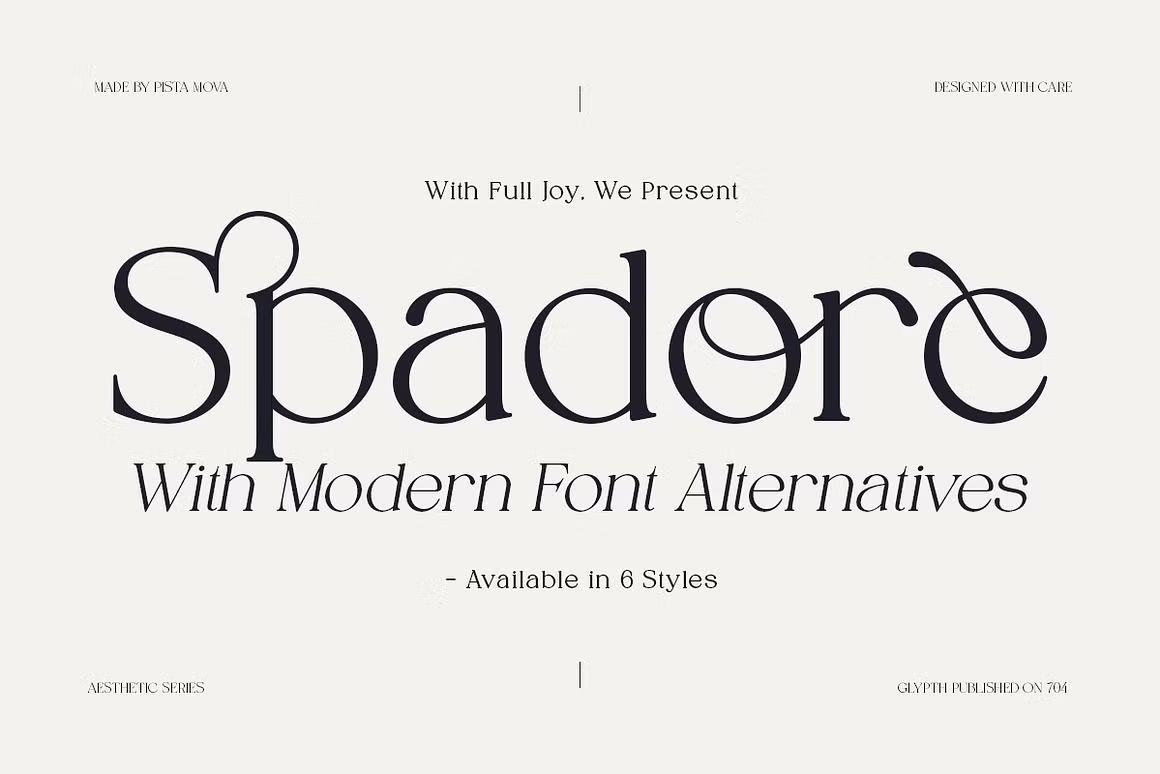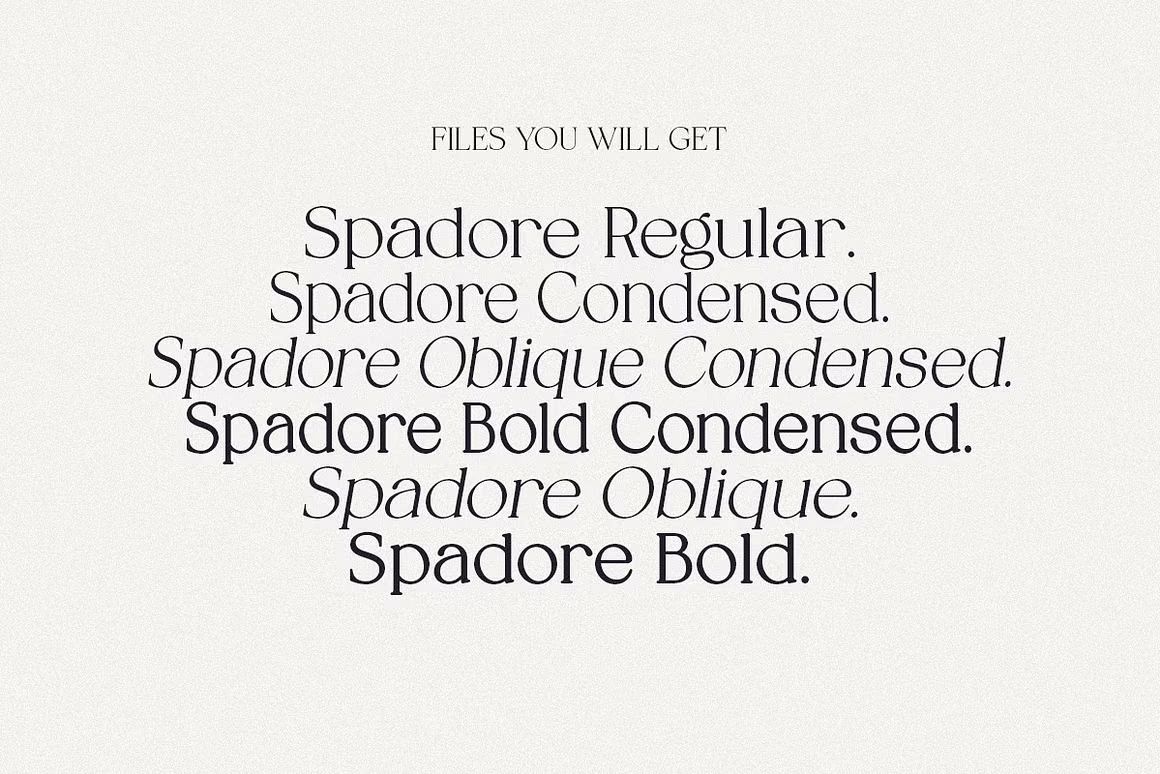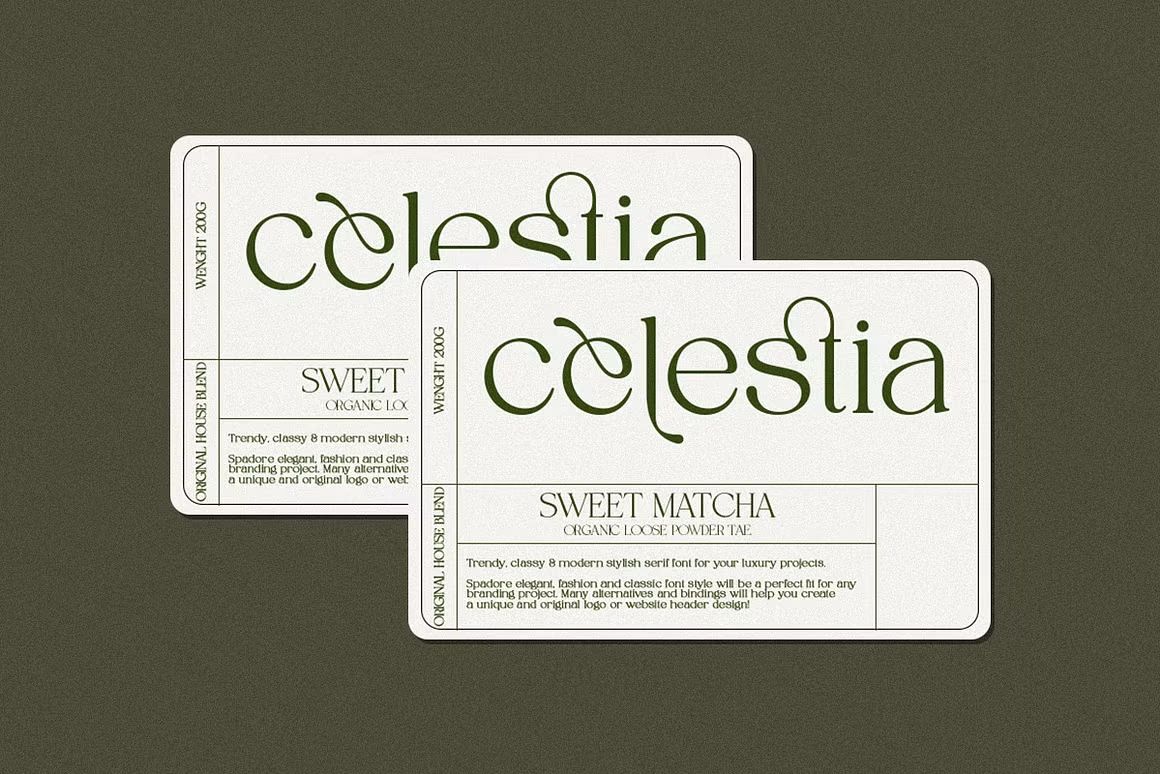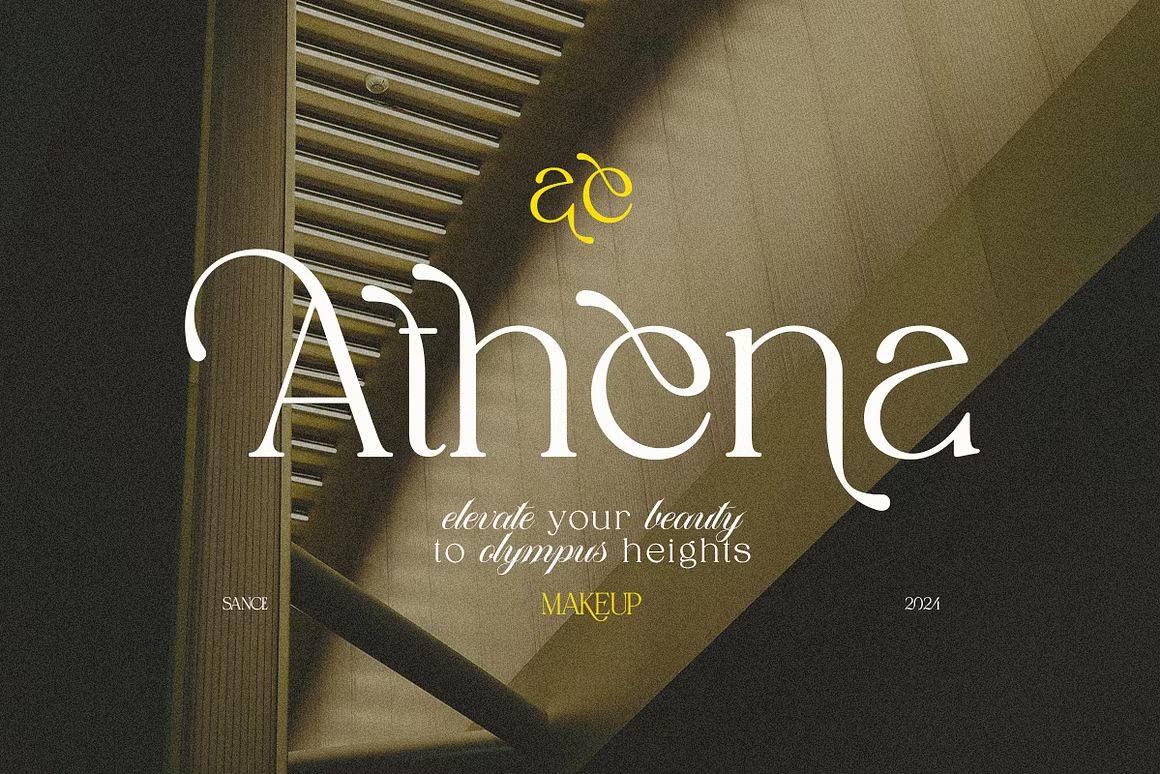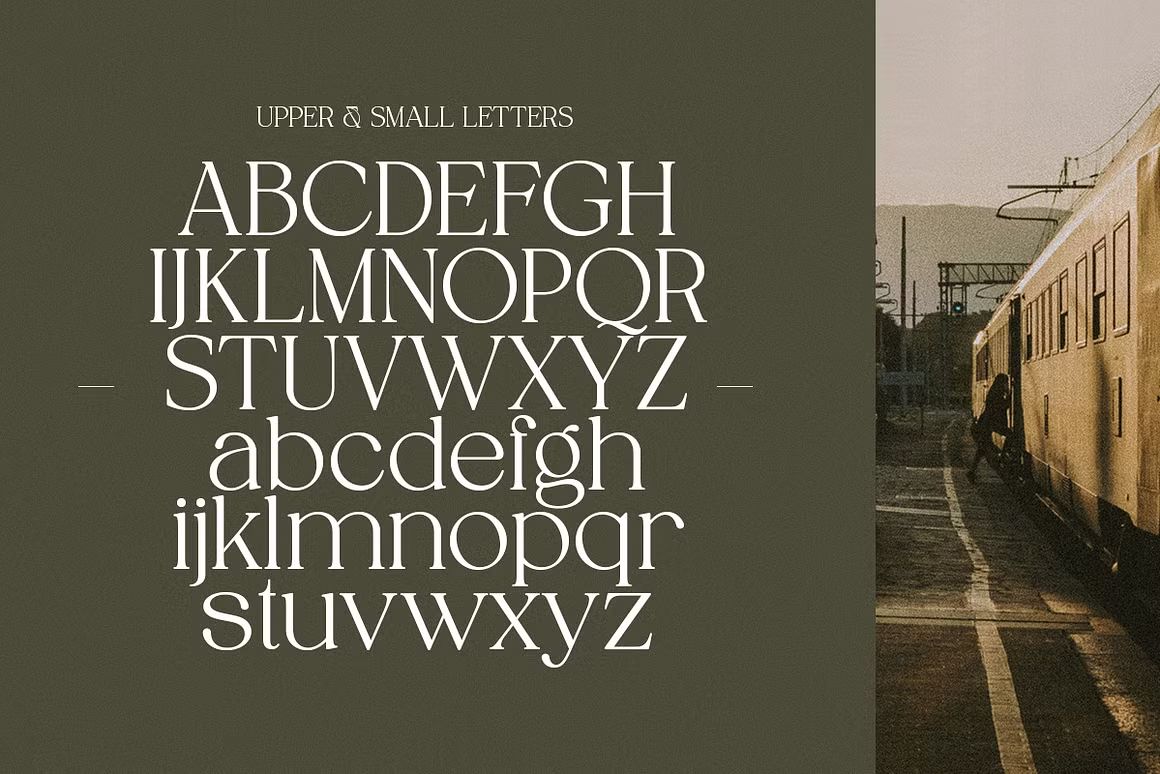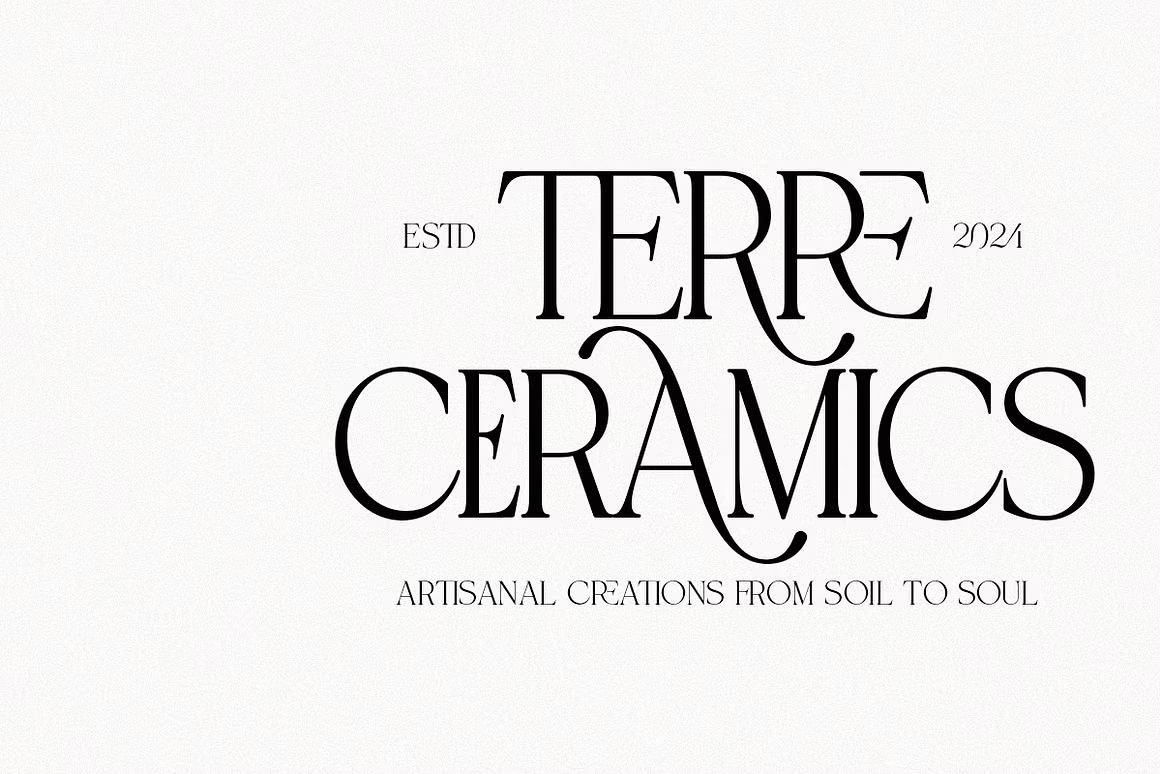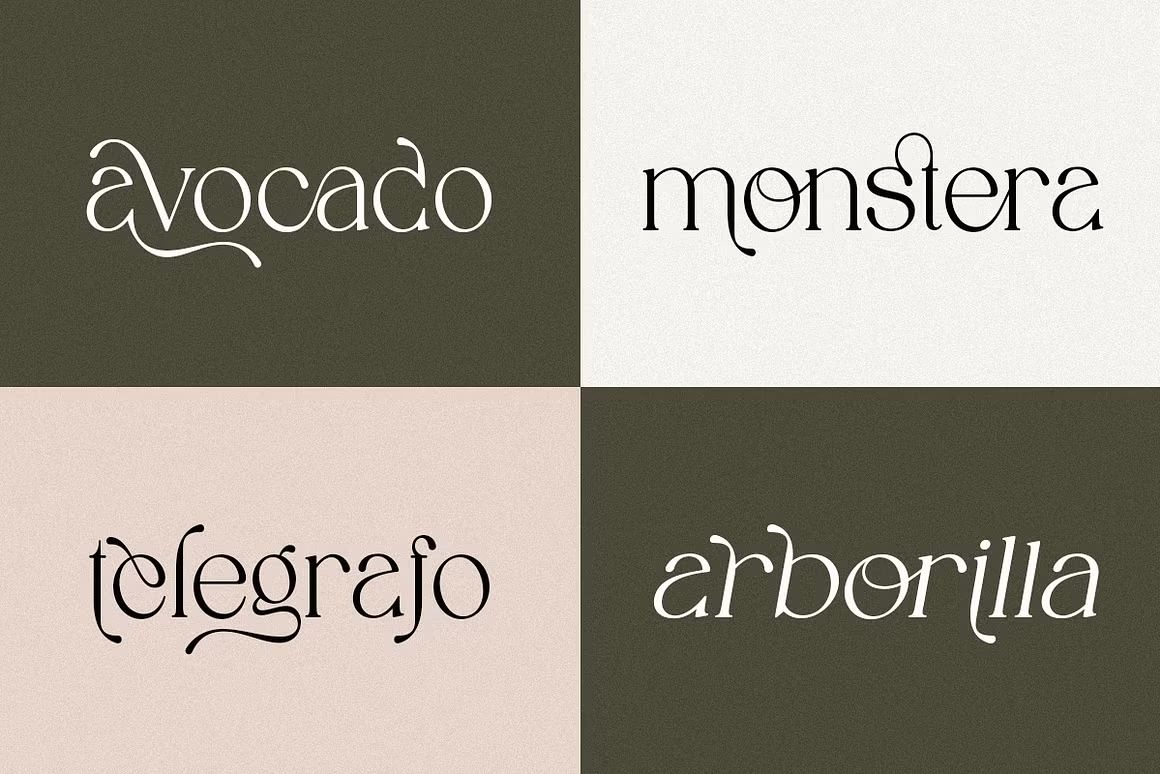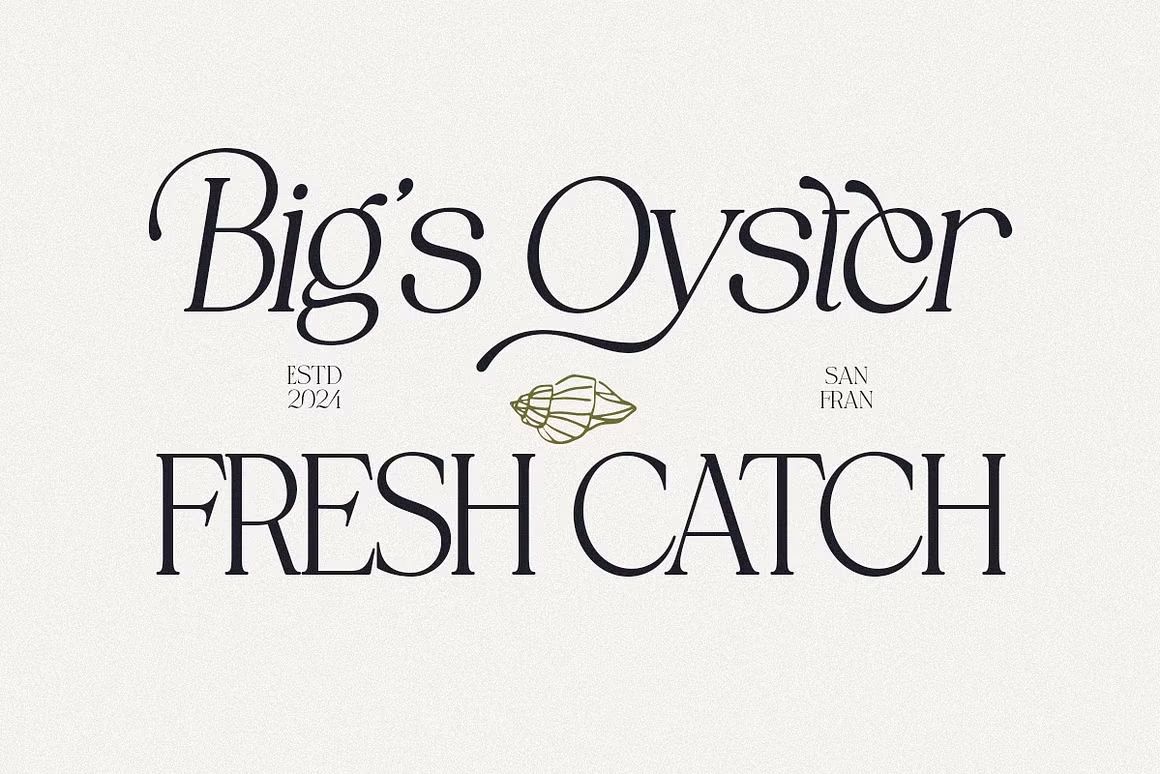
Spadore – Sans Serif Font
Spadore adalah font sans serif bergaya modern dan minimalis dengan bentuk huruf yang bersih, tegas, dan proporsional. Didesain untuk tampil elegan namun tetap sederhana, Spadore cocok digunakan dalam berbagai proyek seperti branding, editorial, web design, kemasan produk, dan presentasi profesional. Font ini memberikan kesan rapi, kontemporer, dan serbaguna.
• Sans serif modern dengan desain bersih dan proporsional
• Ideal untuk branding, editorial, dan desain digital
• Termasuk huruf besar, kecil, angka, dan simbol